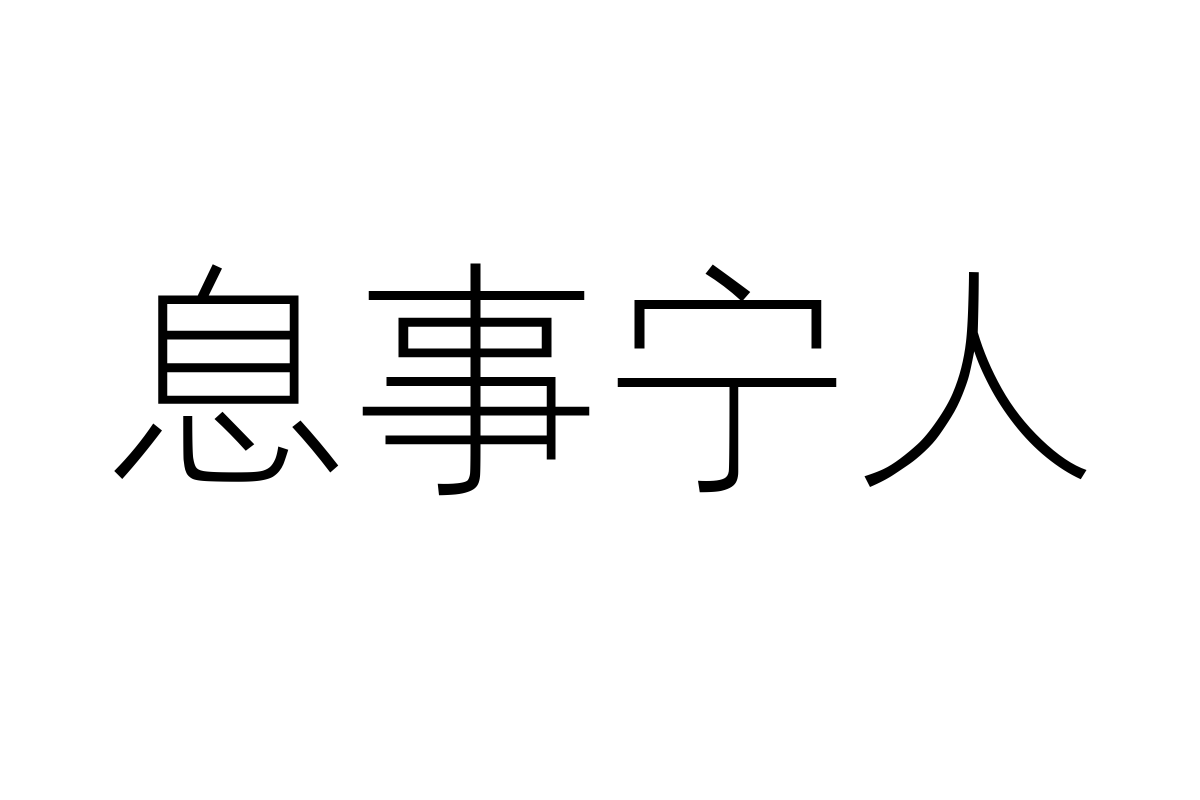
汉仪细简黑简是一款具有现代感的中文字体,它以其独特的设计和优雅的线条而受到许多设计师和品牌的青睐。这款字体的特点如下:
1. 简洁性:汉仪细简黑简的设计非常简洁,没有多余的装饰,这使得它在视觉上更加清晰和易于阅读。
2. 现代感:这款字体的线条流畅,给人一种时尚、现代的感觉,非常适合用于需要展现现代感和科技感的场合。
3. 可读性:由于其简洁的设计,汉仪细简黑简的可读性非常高,无论是在网页设计还是在其他任何形式的文本排版中,都能保证信息的清晰传达。
4. 适应性:这款字体适用于各种类型的文本排版,包括标题、正文、广告等,具有很强的适应性。
总之,汉仪细简黑简是一款既美观又实用的中文字体,非常适合用于需要展现现代感和科技感的各种场合。